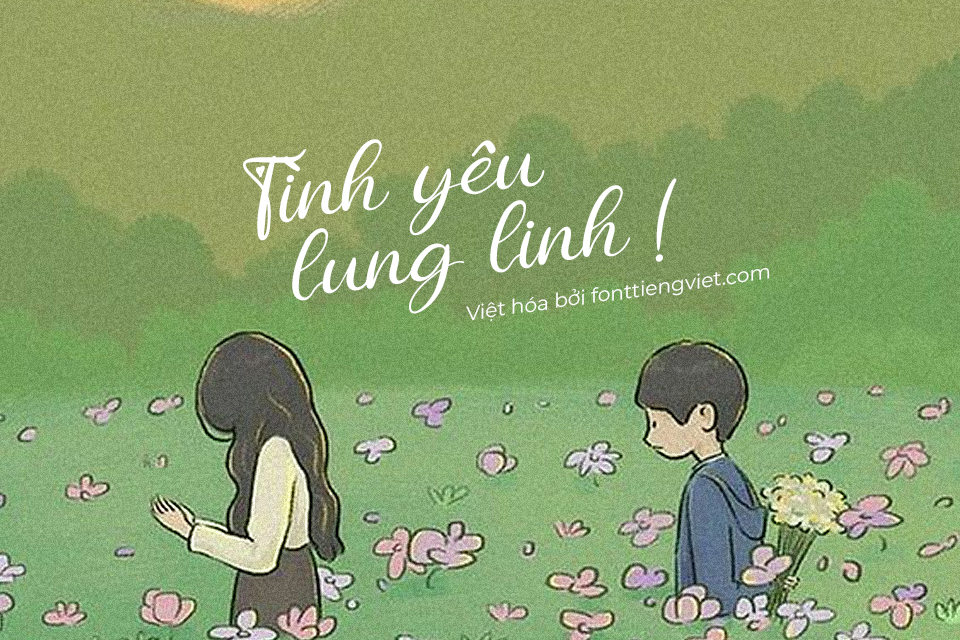
Font việt hóa 1FTV Darinella
Font việt hóa 1FTV Darinella – Sự lựa chọn tinh tế cho thiết kế hiện đại
Giới thiệu về Font việt hóa 1FTV Darinella
Trong thế giới đồ họa đa dạng, việc tìm kiếm một bộ Font Miễn Phí chất lượng luôn là ưu tiên hàng đầu của các nhà thiết kế. Font việt hóa 1FTV Darinella nổi lên như một giải pháp hoàn hảo, mang đến sự kết hợp giữa nét chữ thanh lịch và khả năng hiển thị tiếng Việt trọn vẹn. Đây là bộ font đặc biệt phù hợp cho những ai đang tìm kiếm phong cách hiện đại nhưng vẫn giữ được nét mềm mại, gần gũi trong từng con chữ.
Đặc điểm nổi bật của Font việt hóa 1FTV Darinella
Phong cách thiết kế độc đáo
Font việt hóa 1FTV Darinella sở hữu đường nét thanh thoát, tạo cảm giác dễ chịu cho người xem. Các ký tự được chăm chút tỉ mỉ, đảm bảo độ tương phản hợp lý giữa các nét thanh và nét đậm. Điều này giúp font chữ không chỉ đẹp mắt trên các bản in mà còn hiển thị sắc nét trên các thiết bị kỹ thuật số như điện thoại hay máy tính bảng.
Tính ứng dụng cao trong giáo dục và đời sống
Với các bạn học sinh và giáo viên, bộ font này là công cụ đắc lực để trình bày bài giảng hoặc làm báo cáo. Sự rõ ràng của Font việt hóa 1FTV Darinella giúp nội dung truyền tải trở nên chuyên nghiệp và dễ tiếp thu hơn. Bạn có thể sử dụng nó cho tiêu đề tiểu luận, thiết kế thiệp mời hoặc các dự án sáng tạo cá nhân một cách linh hoạt.
Cách sử dụng Font việt hóa 1FTV Darinella hiệu quả
Để tận dụng tối đa vẻ đẹp của Font việt hóa 1FTV Darinella, bạn nên kết hợp nó với các tông màu trung tính hoặc pastel. Việc điều chỉnh khoảng cách dòng và chữ (kerning) cũng rất quan trọng để tạo ra sự cân đối tổng thể. Đừng ngần ngại thử nghiệm font chữ này trong các phần mềm thiết kế như Canva, Photoshop hay đơn giản là trong Word.
Kết luận về bộ font chất lượng